汉字的美蕴含着中国人的气质与五千年的文化沉淀。中国汉字的历史是长达数千年的发展和演变的历史过程,从先秦、秦、汉、唐时期文字、宋元时期、明清文字、中国近代文字和中国现代文字不断演变。而今已有多种多样的字体,今天小编要给大家推荐的是具有代表性的现代感十足的中国艺术字。
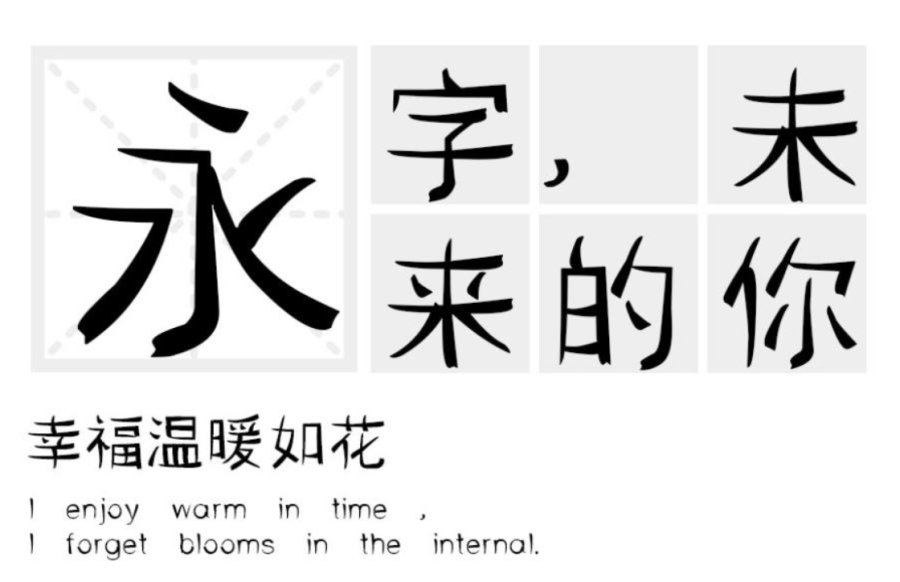
图片识别字体知道这款字体叫做“汉标甩袖体”,它为什么叫做这个名字呢?因为这款字体像一个正在甩动袖子的人,它萃取人类曼妙的肢体语言,呼唤人字合一的书写精神。让文字宛如从心里流出,原来朴素才最有力量!通过笔画的角度和曲线的密切关系,使字体表现出甩袖形体的美感。
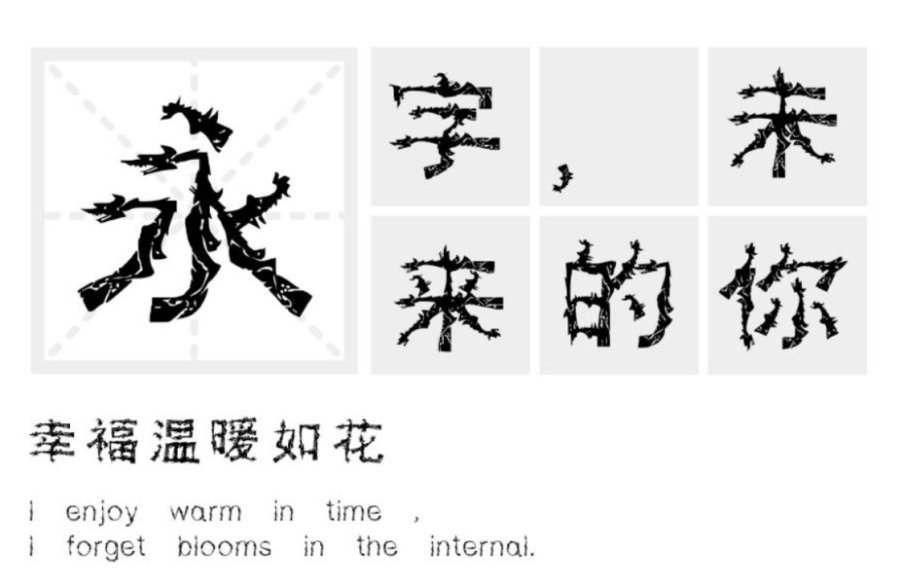
这款具有极强中国元素的字体叫做“汉标华夏龙体”通常字形中的点、撇、捺、钩、提等笔画各具面目,笔画运用了龙图形元素来构建,把这些笔画做成了龙,概括为飘逸的龙型,并且使左右舒展的笔画尽量对称,最大限度地简化笔画龙造型。
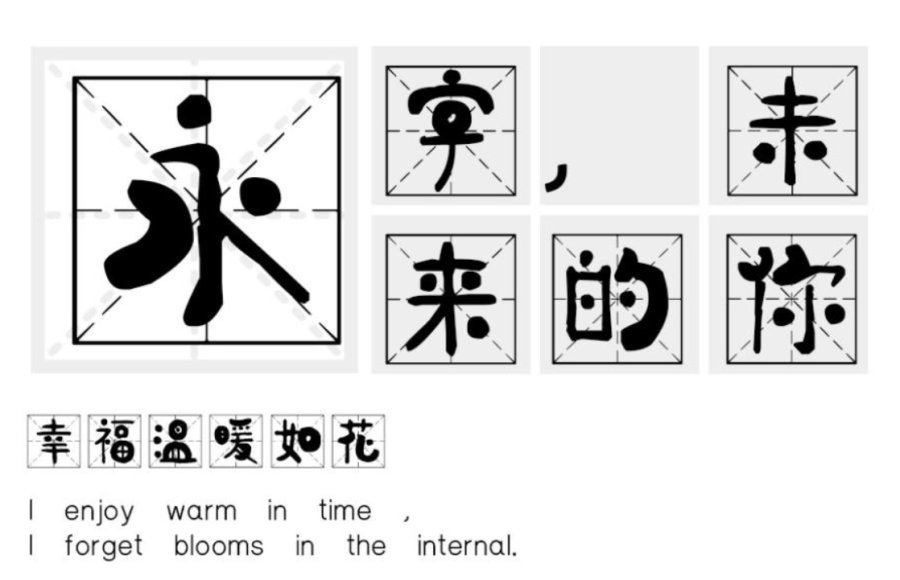
这款“汉标燕赵米格体”带口元素的字基本书写成了圆圈,竖为细,软件制作了米格,既遒劲有力又不失文雅风韵的特色字体。适用于少儿识图认字,文艺类的书刊、品牌广告和产品包装设计,以及社交网络的个性化用字。
世界上还没有任何一种文字像汉字这样经久不衰,大家幼时从田字格开始,在那个方正大方的格子里,我们一遍遍地抄写汉字,一遍遍地模仿一笔一划。到现时代中国字的艺术设计持续发展为设计助力。保存图片点击看图找字可以了解以上三款字体字体的多样呈现,设计独树一帜的中国风。